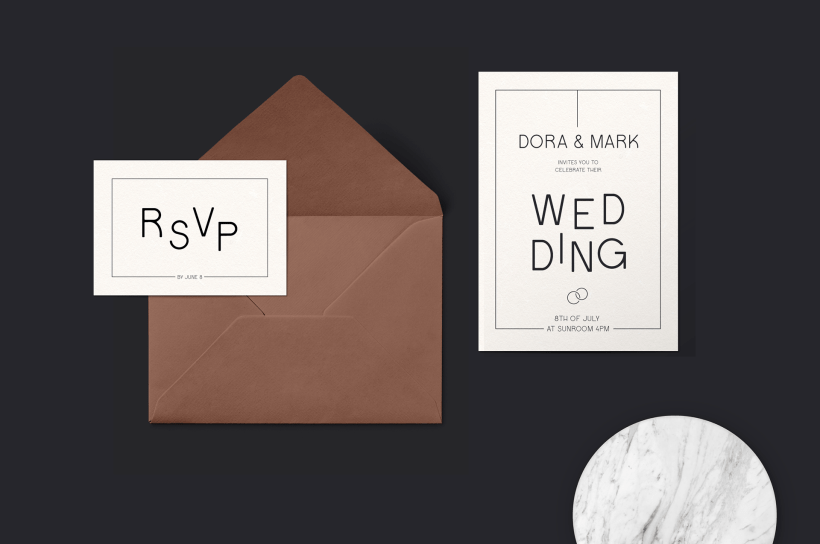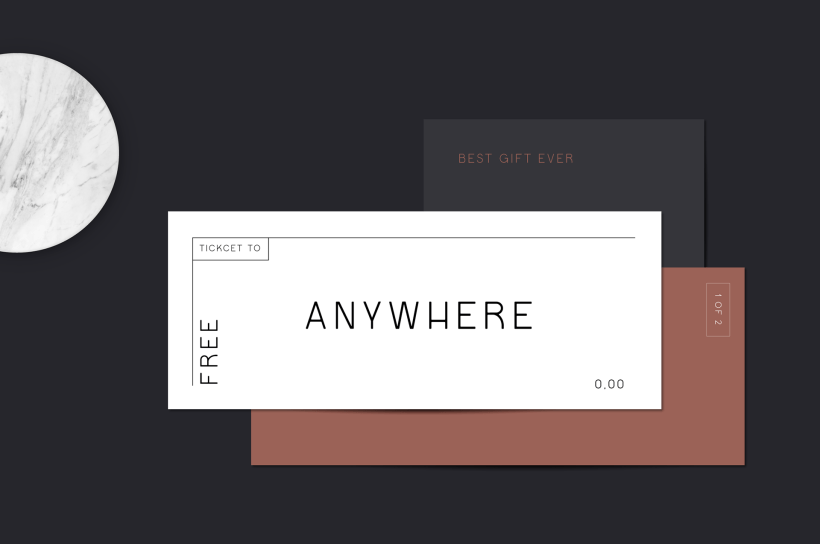
Typographie gratuite : Quint de WildOnes Design
La police gratuite Quint Uppercase a une construction géométrique avec des détails ronds pour former des lettres élégantes. Le style moderne et contemporain avec des détails rétro en fait un excellent choix pour les titres, les logotypes, les affiches et les magazines.